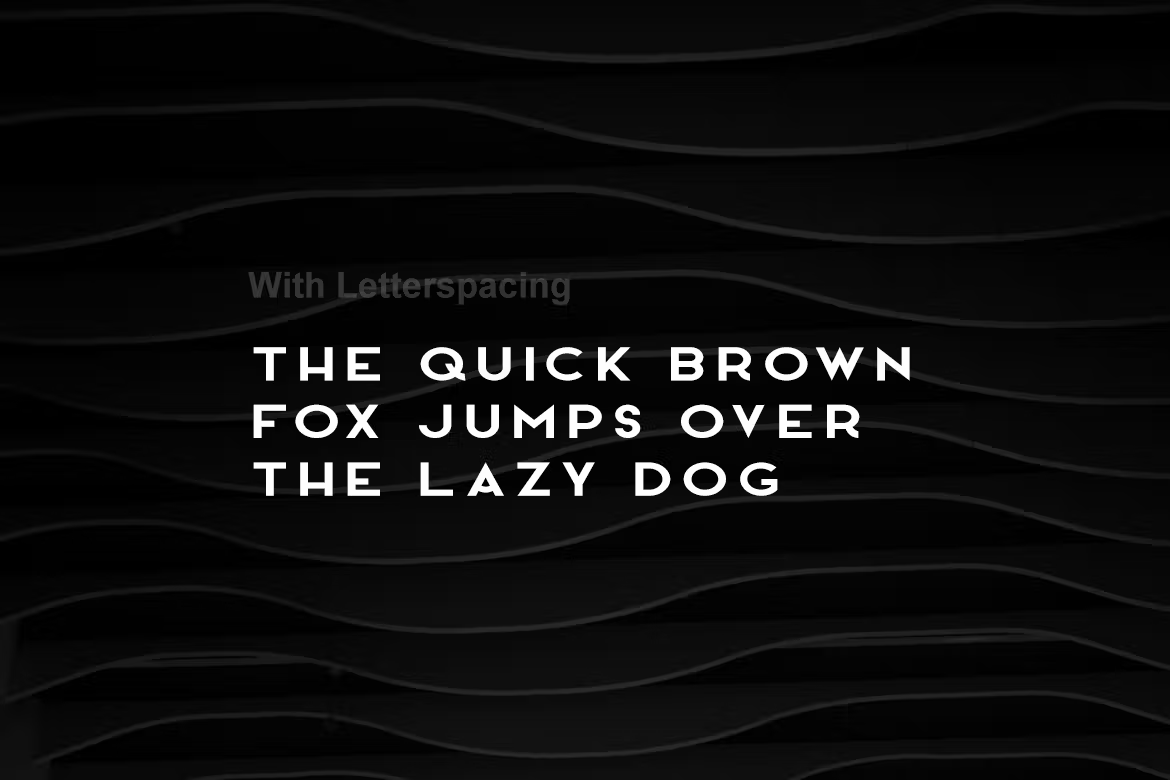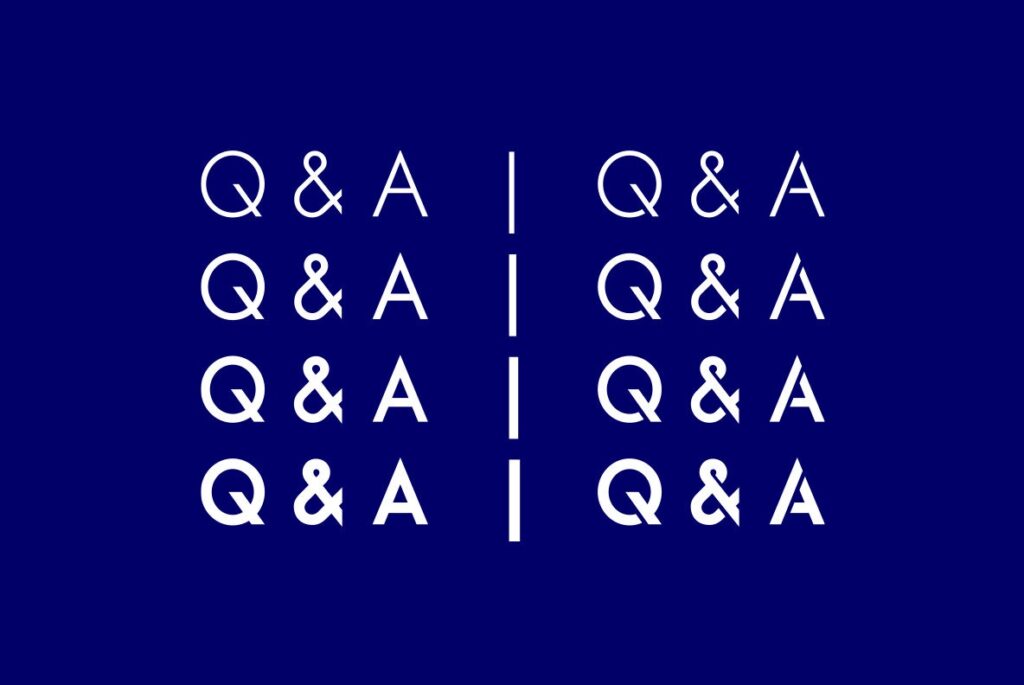
HANOVER Typeface Font
Un moderne & police minimaliste spécialement conçue pour le luxe, la mode et le style avec sa touche unique qui la rend parfaite pour les beaux titres, les marques, les logos et les logos. utilisation de l’affichage. Cette police tout en majuscules est également parfaite pour créer des logos, du contenu promotionnel et des graphiques marketing exceptionnels qui peuvent vraiment attirer l’attention de vos visiteurs.
Ajoutez un espacement des lettres pour créer des titres uniques – un cas d’utilisation essentiel de la tendance du design minimaliste moderne. Veuillez consulter les exemples ci-dessus pour avoir une idée des capacités de cette police.
HANOVER est livré avec 4 graisses (Thin, Light, Regular et Bold) ainsi que des versions italiques des 4 graisses. Le pack contient les polices OTF, TTF et Web (toutes les EOT, SVG, TTF, WOFF, WOFF2 sont incluses) comme options de licence.